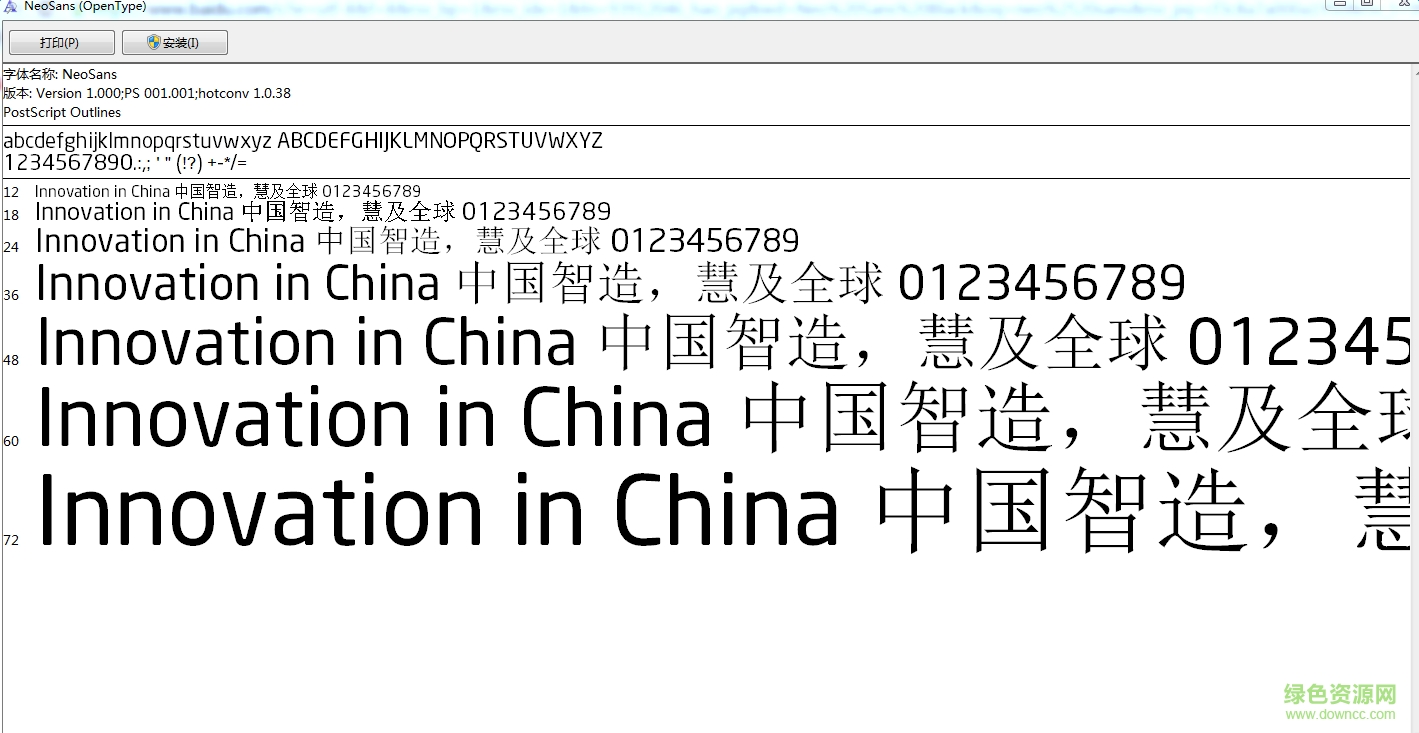
neo sans字體是一款經(jīng)典的英文字體,筆畫均勻,線條優(yōu)美,帶有獨(dú)特的韻味,常常用于時(shí)尚雜志或廣告宣傳方面,對(duì)這款字體有興趣的小伙伴趕緊下載吧!
Neo Sans曾經(jīng)作為intel的御用字體而風(fēng)靡一時(shí)。Neo Sans這個(gè)04年才產(chǎn)生的字體比起其他經(jīng)典英文字體算是“后輩”,但也因此有著現(xiàn)代感的優(yōu)美的弧度。也許是因?yàn)樵?jīng)有過和intel的合作,這種字體帶著濃濃的科技感。Neo Tech是Neo Sans的變體,某些字母更加簡約和現(xiàn)代。